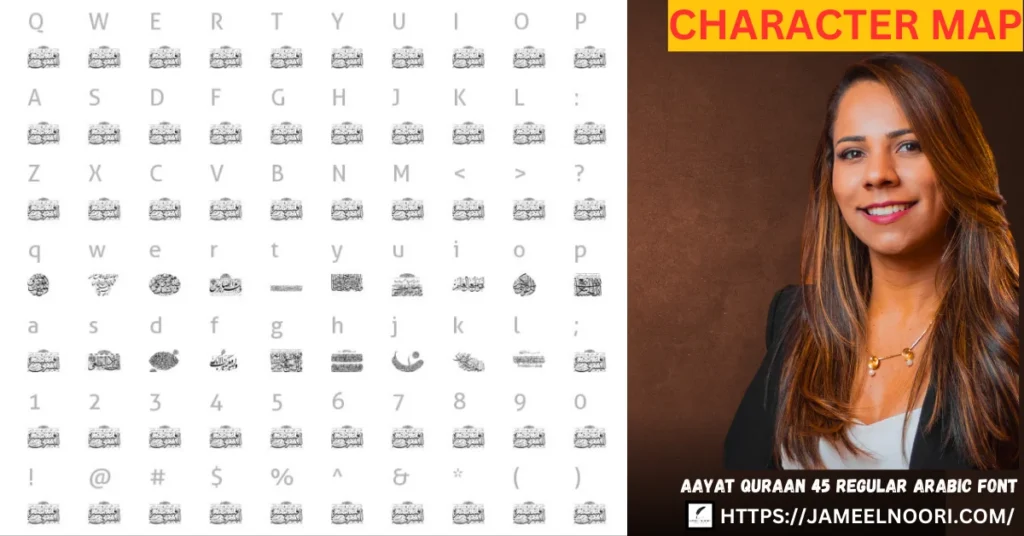
Aayat Quraan 45 Regular Arabic Font – Widely-Used Islamic Font
Aayat Quraan 45 Regular Arabic Font aik bohot mashhoor aur widely-used Islamic Arabic font hai jo Quranic calligraphy ke liye perfect mana jata hai. Ye font Pakistan, Lahore aur Karachi ke users me khas taur par famous hai kyunke iska design clean, readable aur bilkul traditional Arabic style me hota hai. Roman Urdu me likhne walon, bloggers, designers, aur Islamic content creators ke liye ye font aik bohot hi valuable choice ban chuka hai.
What Is Aayat Quraan 45 Regular Arabic Font? – Ultimate Overview
Best Features of Aayat Quraan 45 Regular Arabic Font (Expert Choice)
StyleQuranic Arabic Calligraphy
Important Highlights:
• Clean aur sharp Arabic glyphs
• Islamic posters, banners aur Quranic designs ke liye perfect
• Har size me readable aur elegant look
• Urdu Fonts aur Arabic Fonts category me top-ranking font
Aayat Quraan 45 Regular Arabic Font Preview & Character Map
Explore the Character Map of Aayat Quraan 45 Regular Arabic Font for Perfect Quranic Calligraphy
Best Uses of Aayat Quraan 45 Regular Arabic Font (Pakistan Friendly Guide)
Is font ka design Quranic text ko mind me rakh kar banaya gaya hai. Yaha kuch perfect use-cases diye gaye hain:
• Quranic Images aur Islamic Posters
• Social Media Islamic Quotes
• Urdu & Arabic Typography
• Madrasa Notes aur Online Islamic Courses
• WordPress Islamic Blogs
• InPage Writing Projects
• Logo aur Branding Material
Is wajah se jab bhi Pakistan me koi Arabic font download karne ka sochta hai, to Aayat Quraan 45 Regular Arabic Font unki top preference hoti hai.
Aayat Quraan 45 Regular Arabic Font Calligraphy & Character Map
Character Map section me aap ko iska complete glyph design milta hai jahan har letter ka Islamic aur Quranic style clearly visible hota hai.
Iski calligraphy:
• Balanced
• Highly readable
• Smooth rounded edges
• Perfect spacing
Ye qualities isay best Arabic font categories me top position deti hain.
Why Pakistan Users Prefer Aayat Quraan 45 Regular Arabic Font? (Expert Review)
• Ye font Islamic content ke liye bilkul ideal hai
• Har device par compatible hai
• Bloggers, designers aur students ke liye easy-to-use
• Lahore aur Karachi ke printing press industries me popular
Aakhir me, agar aap Pakistan me ho aur Aayat Quraan 45 Regular Arabic Font ka best Islamic ya Quranic use karna chahte ho, to ye font aap ke liye perfect choice hai. Iska smooth design, compatibility aur readability isay Urdu Fonts aur Arabic Fonts categories me top-ranked banata hai. Ye font bilkul un users ke liye ideal hai jo professional appearance chahte hain without any complexity.
What is Aayat Quraan 45 Regular Arabic Font?
It is a TrueType Arabic calligraphy font commonly used for Quranic and Islamic designs.
Is this font good for Quranic quotes?
Absolutely, it is one of the best fonts for Islamic and Quranic content.
Does this font support diacritic marks?
Yes, it supports complete Arabic vowel marks.